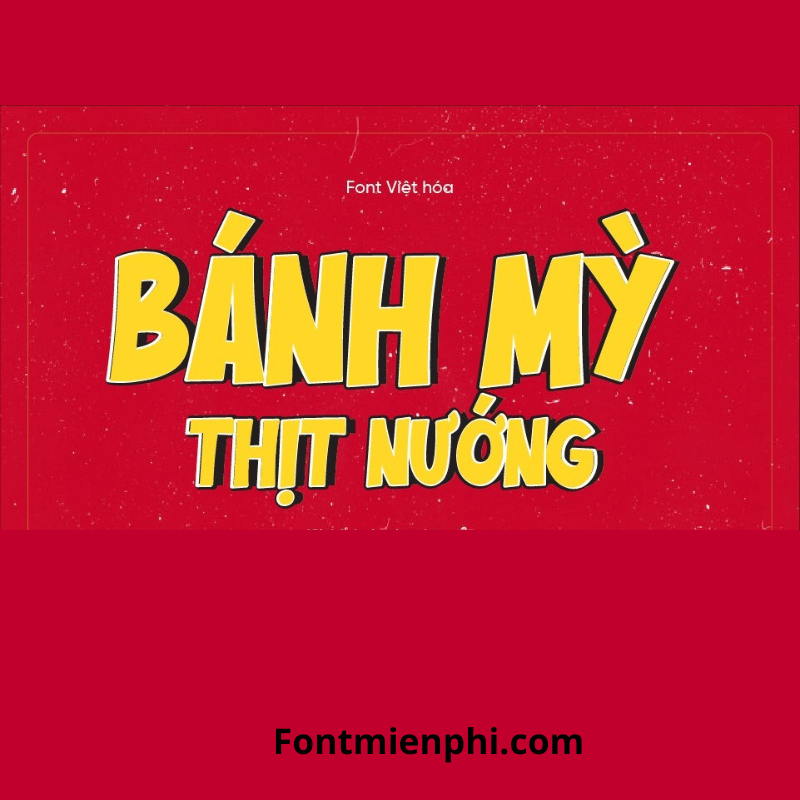
Giới thiệu về Font Việt hóa 1FTV VIP Bazinga!
Chào mừng các bạn đến với thế giới sáng tạo của những con chữ đầy cá tính. Trong bộ sưu tập tài liệu thiết kế dành cho học đường, Font Việt hóa 1FTV VIP Bazinga! nổi lên như một lựa chọn hàng đầu nhờ phong cách hiện đại và vui nhộn. Khi sử dụng Font Miễn Phí này, các thầy cô và học sinh có thể dễ dàng tạo ra những bài giảng điện tử sinh động hoặc các tấm thiệp chúc mừng độc đáo. Đây là bộ phông chữ đã được tinh chỉnh kỹ lưỡng về dấu tiếng Việt, đảm bảo không xảy ra lỗi hiển thị khi soạn thảo văn bản trên các phần mềm phổ biến hiện nay.
Đặc điểm nổi bật của Font Việt hóa 1FTV VIP Bazinga!
Thiết kế năng động và dễ đọc
Đúng như tên gọi lấy cảm hứng từ những câu nói đầy năng lượng, bộ Font Việt hóa 1FTV VIP Bazinga! sở hữu các đường nét bo tròn và độ dày vừa phải. Điều này giúp nội dung trở nên dễ tiếp cận hơn với các em học sinh nhỏ tuổi, đồng thời tạo cảm giác thân thiện trong môi trường sư phạm. Các ký tự được thiết kế đồng nhất, mang lại sự cân bằng tuyệt vời giữa tính thẩm mỹ và công năng sử dụng thực tế trong in ấn học đường.
Ứng dụng đa dạng trong học tập
Với bộ phông chữ này, bạn có thể thiết kế tiêu đề cho các tờ báo tường, làm nhãn vở hay trang trí các slide thuyết trình Powerpoint thêm phần bắt mắt. Khả năng tương thích cao trên cả Windows và macOS giúp người dùng tiết kiệm thời gian cài đặt. Việc sở hữu một phông chữ chuẩn Việt giúp thông điệp giáo dục được truyền tải trọn vẹn và chuyên nghiệp hơn bao giờ hết.